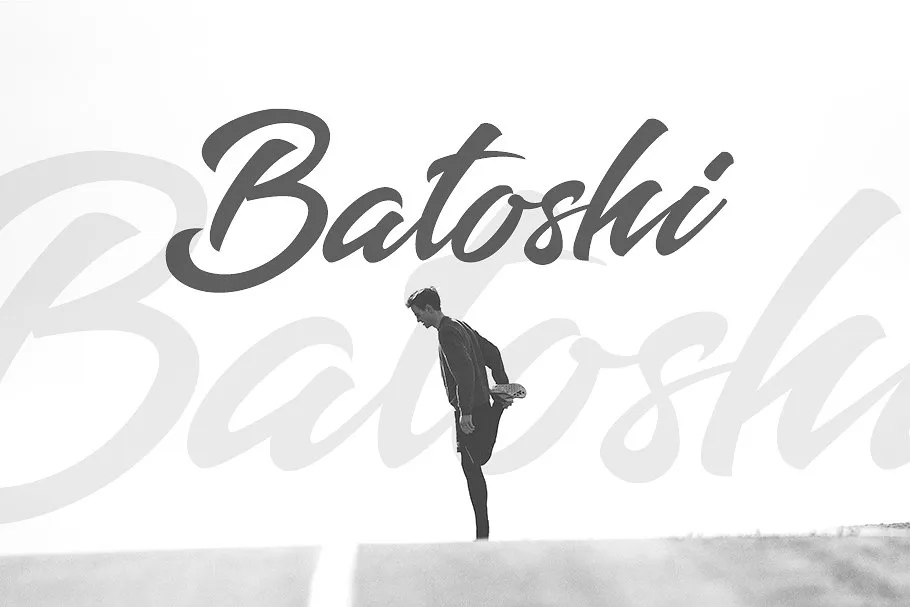
Batoshi Brush Font – Download Grátis
A fonte Batoshi Brush é uma opção intrigante para quem busca algo com cara de arte moderna e natural. Ela se destaca na categoria de script fonts, apresentando desenhos elegantes que remetem à escrita chinesa ou caligrafia oriental. Desenvolvida por 178-MC, Batoshi Brush é ideal para uso em logotipos, marcas de marca e designs gráficos variados como cartazes, embalagens de produtos, capas de livros e menus. Sua proposta é inovadora e atraente, projetada não apenas para ser usada em design editorial tradicional, mas também em criações mais criativas como camisetas personalizadas e materiais publicitários. Engajando-se com os amantes do estilo hand-lettered, Batoshi Brush está aqui para revolucionar o universo da letra brush.